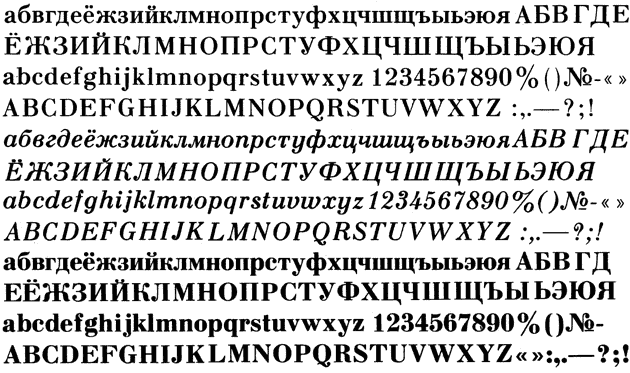
Шрифт Тип Бодони, сделанный в ОНШ (Отделе наборных шрифтов) НИИ Полиграфмаше в конце 70-х годов для фотонабора. Авторы шрифта — Светлана Ермолаева и Людмила Ерошкина.